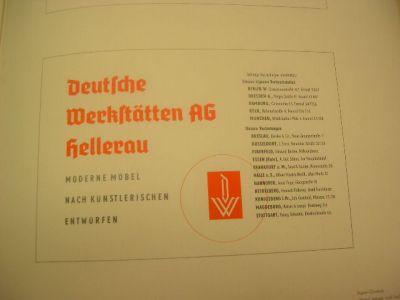
Meiner Meinung nach wurde die Tannenberg nicht aus politischen Gründen geschaffen.
Schriften, die „Tannenberg“ und „National“ heißen, wurden sicher nie und nimmer aus politischen Gründen geschaffen ...
Meiner Meinung nach wurde die Tannenberg nicht aus politischen Gründen geschaffen.
Schriften, die „Tannenberg“ und „National“ heißen, wurden sicher nie und nimmer aus politischen Gründen geschaffen ...
Dass diese Schriften national-chauvinistische Namen tragen und wahrscheinlich in diesem Geist entstanden sind, ist ja offensichtlich; das schließt aber m. E. die These nicht aus, dass es sich um ‹neusachlich› überarbeitete gebrochene Schriften handelt (dass allerdings die «Helvetica» aus den Zwanziger- bzw. Dreißigerjahren stammte, Ligaturix, wäre mir neu…). Das führt mich zu der Frage zurück: Ist diesen Schriften das Martialische und Chauvinistische von der Form her inhärent (wie es u. a. HP Willberg behauptet) oder haben wir uns angewöhnt, diese Anmutungen in die Form hineinzulesen?
>dass allerdings die «Helvetica» aus den Zwanziger- bzw. Dreißigerjahren
> stammte, Ligaturix, wäre mir neu…
Die Neue Haas Grotesk ist erstmals circa 1957 in der Schweiz gezeichnet geworden.
Die von D. Stempel AG/Linotype zusammenübergearbeitete Schrift, "Helvetica", kam ca. 1961 auf dem Markt. Obwohl sie ähnlichkeiten mit Groteskschriften aus den vorherigen Hundertjahren teilt, ist sie keine Schrift, die mit dem 20ern Label bezeichnet könnten.
Die 20ern waren eigentlich die Geburtstunde geometrischer Serifenlosenschriften (also, eine völlige andere Richtung als die ältere Grotesk-Bewegung) wie z.B. die Erbar, Futura, Kabel, und Gill Sans (die eben auch sehr "humanistisch" wirkt… eine Richtung, dass nach dem 2. Weltkrieg richtig los ging).
Meiner Meinung nach wurde die Tannenberg nicht aus politischen Gründen geschaffen.
Schriften, die „Tannenberg“ und „National“ heißen, wurden sicher nie und nimmer aus politischen Gründen geschaffen ...
Dass diese Schriften national-chauvinistische Namen tragen und wahrscheinlich in diesem Geist entstanden sind, ist ja offensichtlich; das schließt aber m. E. die These nicht aus, dass es sich um ‹neusachlich› überarbeitete gebrochene Schriften handelt (dass allerdings die «Helvetica» aus den Zwanziger- bzw. Dreißigerjahren stammte, Ligaturix, wäre mir neu…). Das führt mich zu der Frage zurück: Ist diesen Schriften das Martialische und Chauvinistische von der Form her inhärent (wie es u. a. HP Willberg behauptet) oder haben wir uns angewöhnt, diese Anmutungen in die Form hineinzulesen?
Wenn Du den Namen "Tannenberg" national-chauvinistisch nennst, gilt das dann auch für z.B. den Trafalgar Square in London? Mit der Nelson-Statue?
Die Grundformen der Helvetica stammen aus dem Jahr 1937, wurde von Max Miedinger entworfen. Näheres zur Entwicklung:
>Die Grundformen der Helvetica stammen aus dem Jahr 1937,
>wurde von Max Miedinger entworfen
Recht hast du, dass diese Formen von Max Miedinger entworfen sind. Aber er hat die 1957 für den Herrn Edouard Hoffman bei Hass gemacht, nicht 1937.
>> Wenn Du den Namen "Tannenberg" national-chauvinistisch nennst, gilt das dann auch für z.B. den Trafalgar Square in London? Mit der Nelson-Statue?
Mit Verlaub: Ein weltberühmter Platz und der Name einer etwas obskuren Schrift sind vielleicht nicht *die* idealen Vergleichsgrößen. Man könnte sich ja eher fragen, ob eine Schrift z. B. mit dem Namen «Agincourt», «Waterloo» oder «Verdun» am Platze sei? Fände ich genauso bedenklich.
Aber Du willst ja wohl wieder auf das vermeintlich verkorkste deutsche Nationalgefühl hinaus («Wieso dürfen wir nicht, was die Engländer und alle anderen dürfen?») – als ob hier alle derart einfach gestrickt denken würden…
>Die Grundformen der Helvetica stammen aus dem Jahr 1937,
>wurde von Max Miedinger entworfen
Recht hast du, dass diese Formen von Max Miedinger entworfen sind. Aber er hat die 1957 für den Herrn Edouard Hoffman bei Hass gemacht, nicht 1937.
Meine Quelle:
Georg Kandler - Alphabete - Erinnerungen an den Bleisatz
Wobei ich die anderen Jahreszahlen auch kenne.
Und so richtig los ging es mit der Helvetica sowieso erst 1961, nachdem Stempel begonnen hatte, die vielen verschiedenen Formen zu entwickeln.
Apropos - eine Frage:
Wenn man eine Korrektur bzw. eine wichtige, grundlegende Ergänzung zur Herkunft einer Schrift per Email an Linotype schickt - bekommt man im Normalfall eine Antwort? Bzw.: Liest diese Email jemand? Oder wird das halbautomatisch als Spam eingestuft und gelöscht?
Das blöde ist: Ich habe im Moment den Namen der Schrift nicht mehr im Kopf. Bei Linotype wird als Herkunft eine ominöse, nicht näher bezeichnete Londoner Foundry genannt. Dabei ist es eine deutsche.
>> Wenn Du den Namen "Tannenberg" national-chauvinistisch nennst, gilt das dann auch für z.B. den Trafalgar Square in London? Mit der Nelson-Statue?
Mit Verlaub: Ein weltberühmter Platz und der Name einer etwas obskuren Schrift sind vielleicht nicht *die* idealen Vergleichsgrößen. Man könnte sich ja eher fragen, ob eine Schrift z. B. mit dem Namen «Agincourt», «Waterloo» oder «Verdun» am Platze sei? Fände ich genauso bedenklich.
…Rettung des Reiches…
Eine Wertung aus heutiger Sicht ist nicht relevant auf eine Assoziation mit dem Wort Tannenberg zum Zeitpunkt des Erscheinens dieser Schrift im Jahr 1934. Nur auf die damalige kam es mir an. Und die damalige war in Bezug auf die Schlacht bei Tannenberg, auf Hindenburg und allgemein auf das Deutsche Reich nationalistisch.